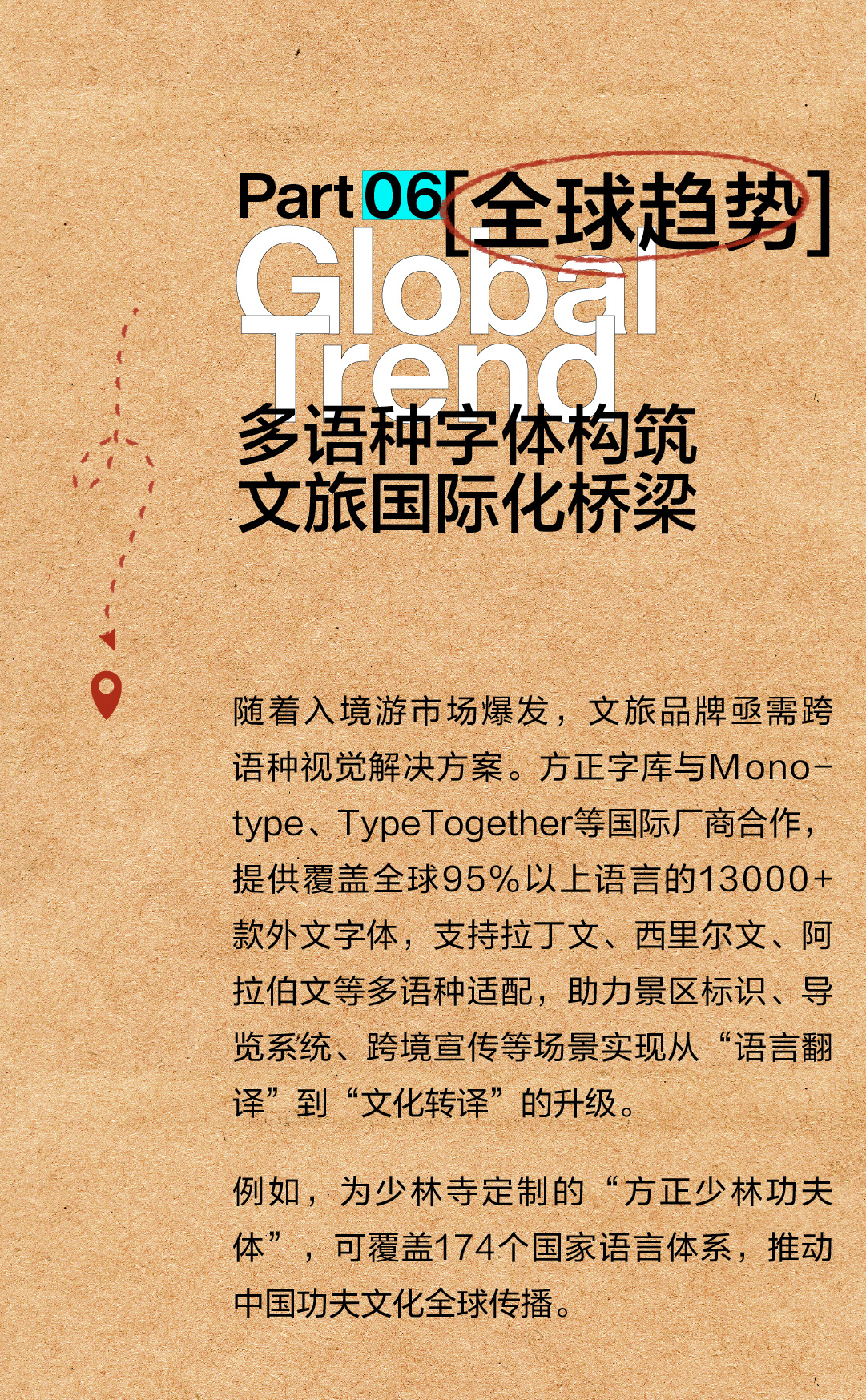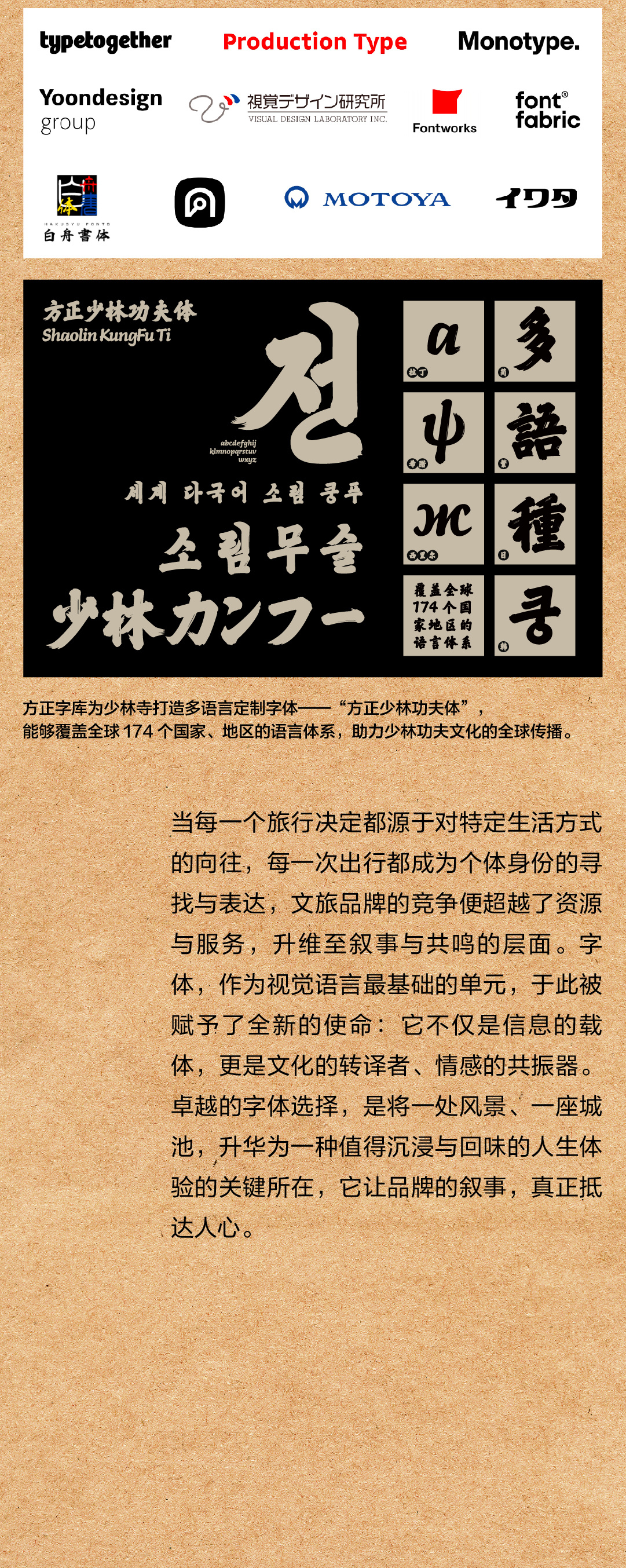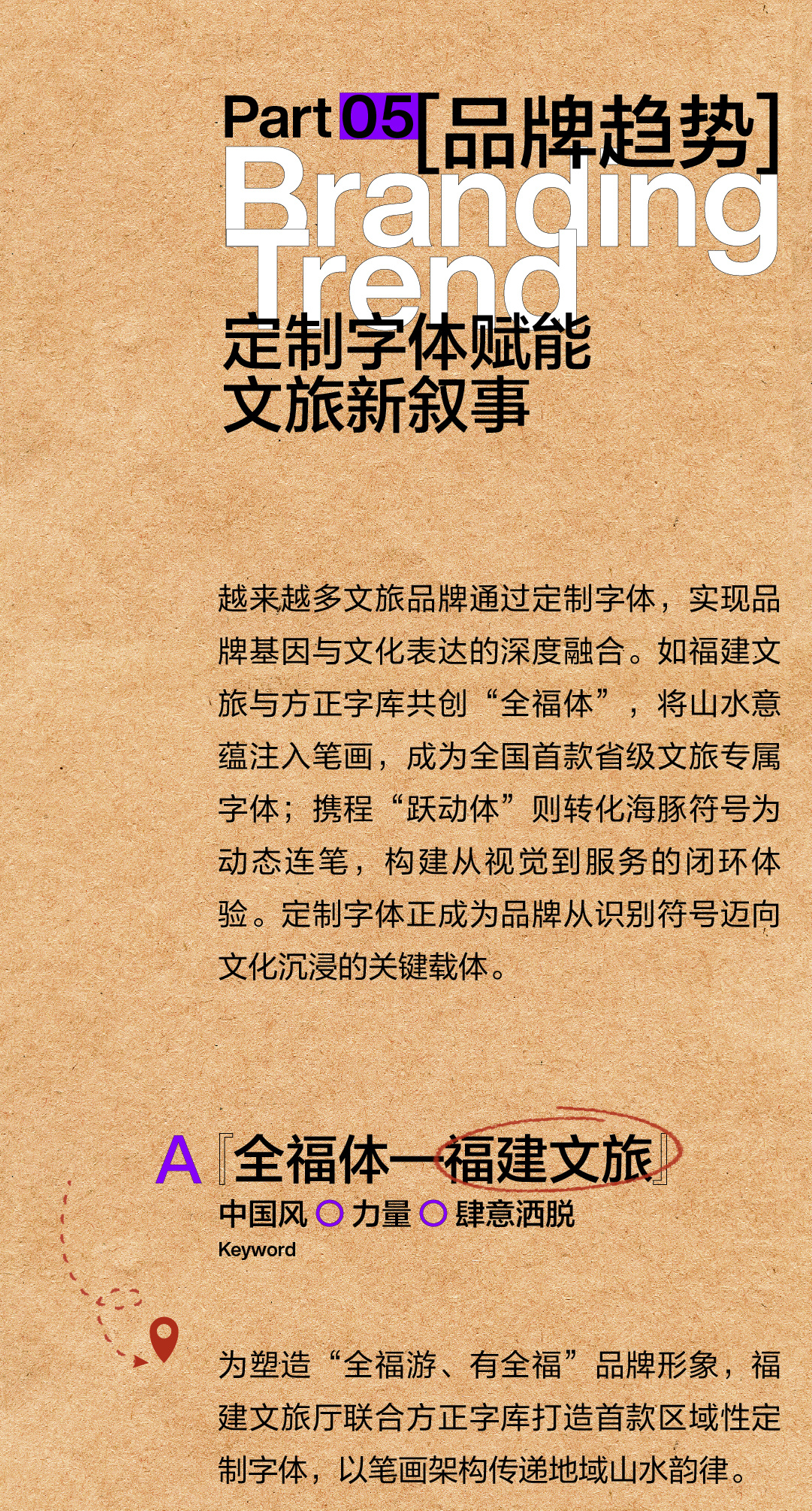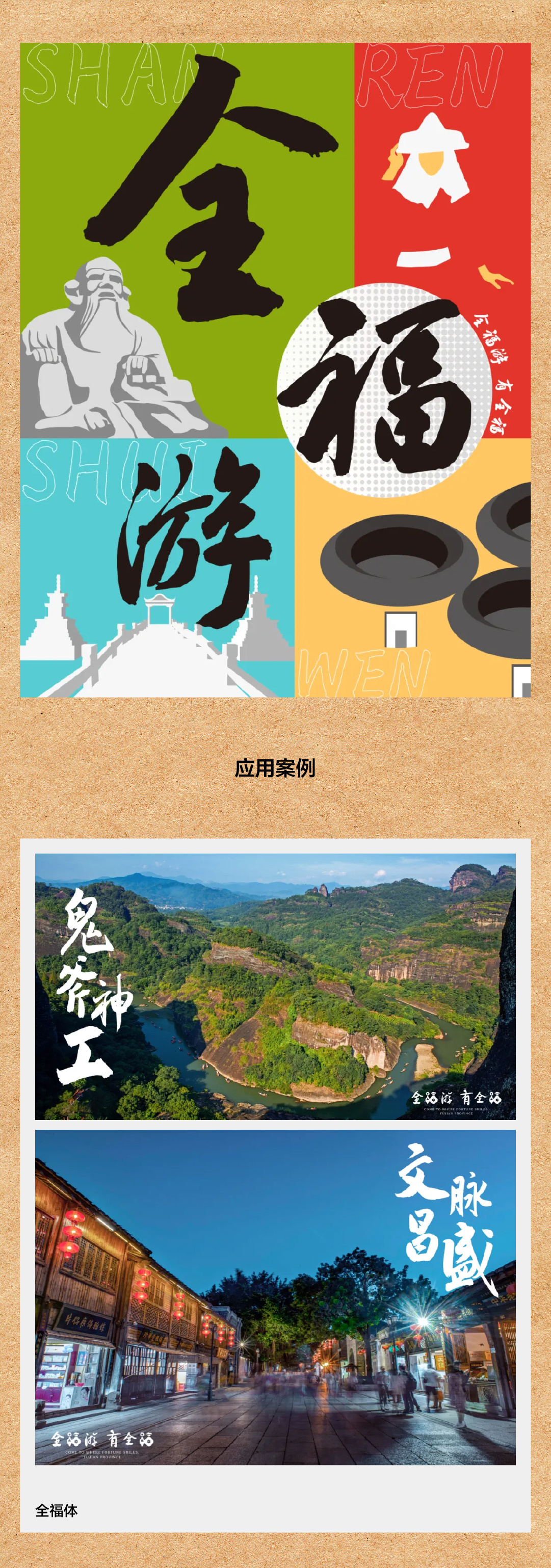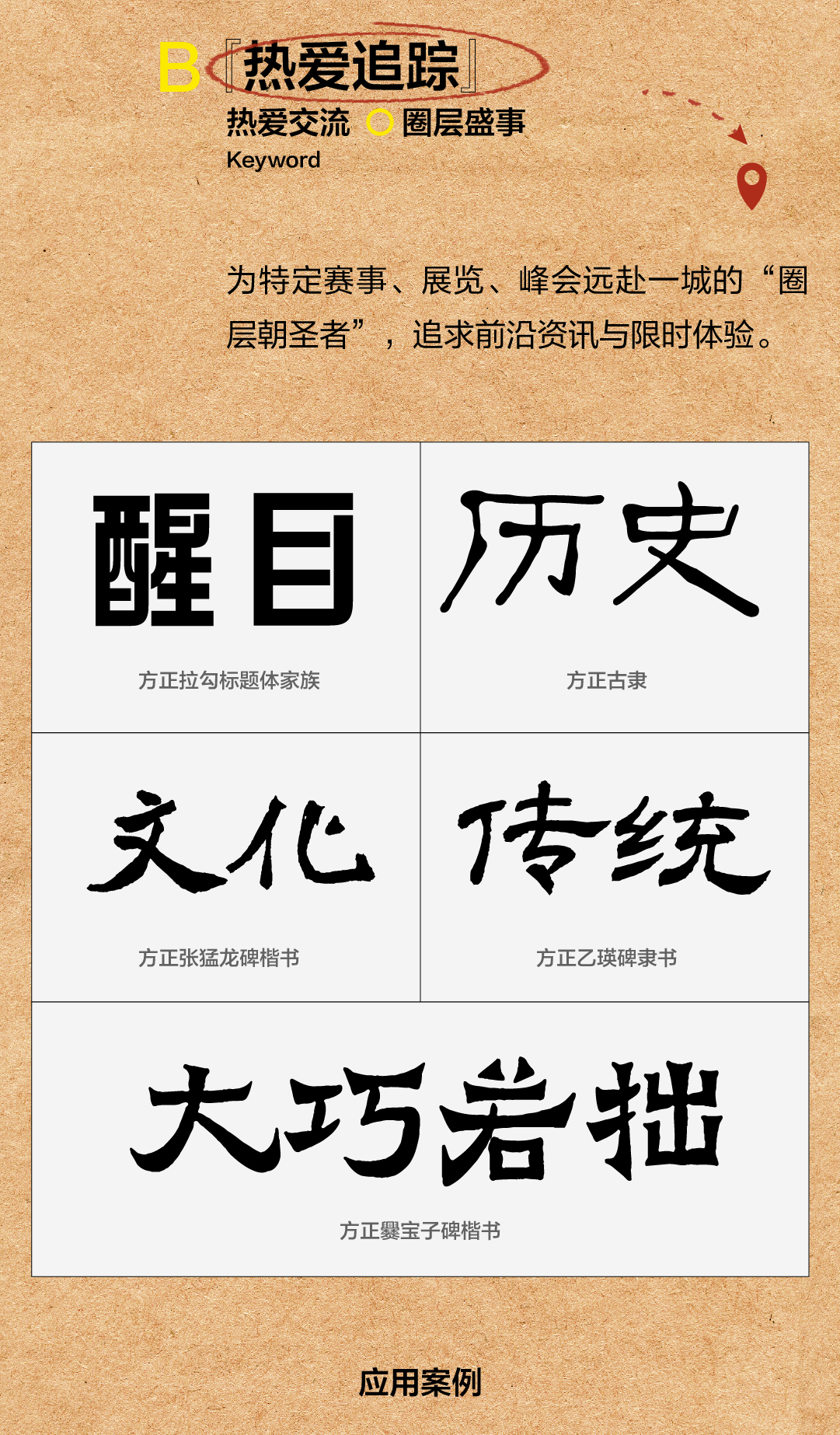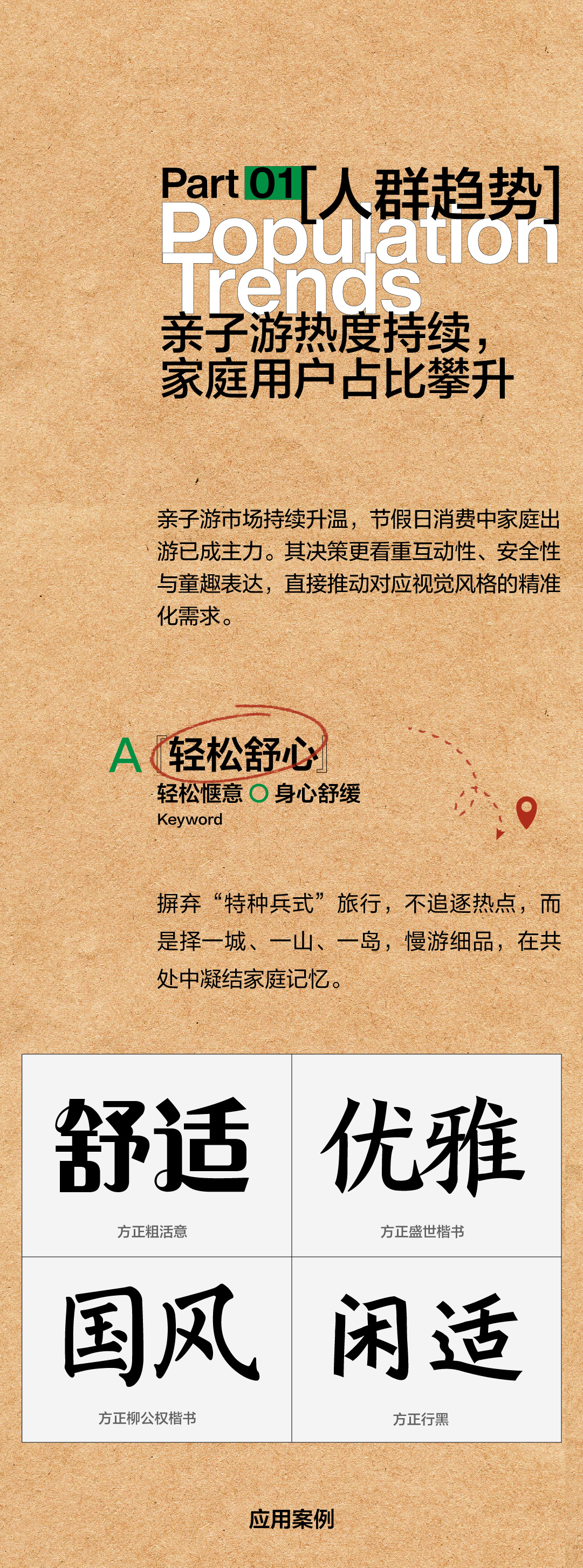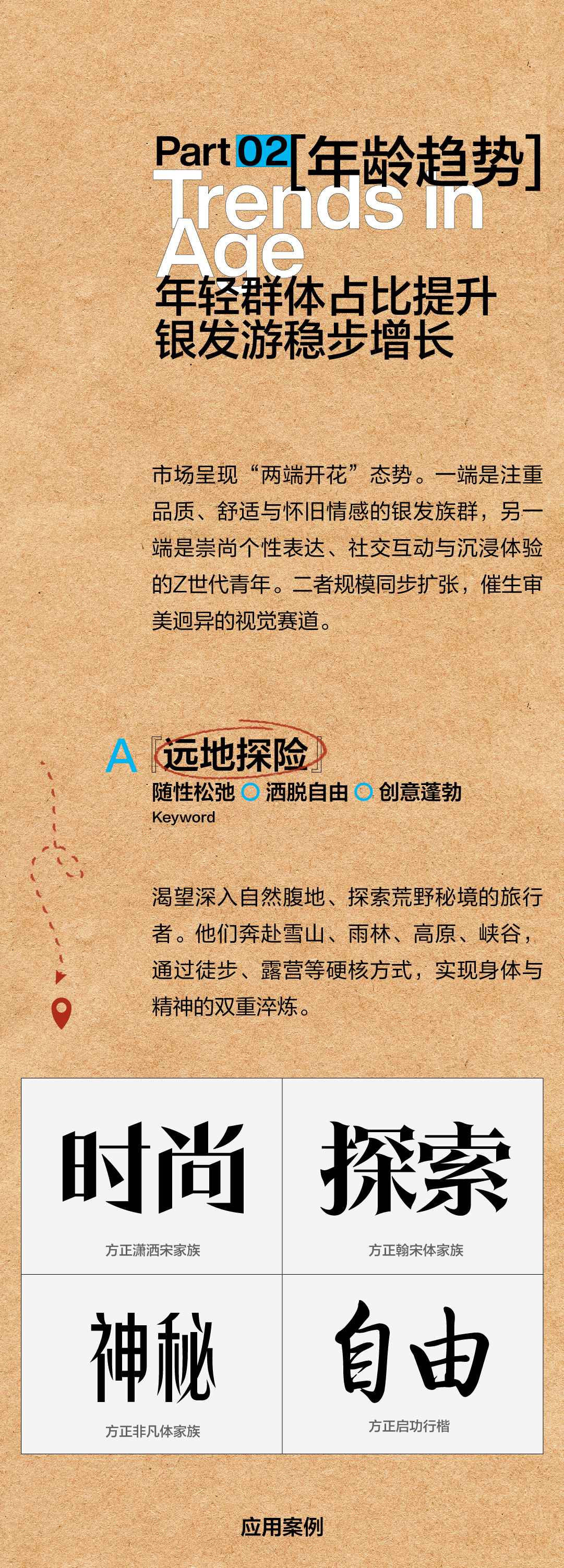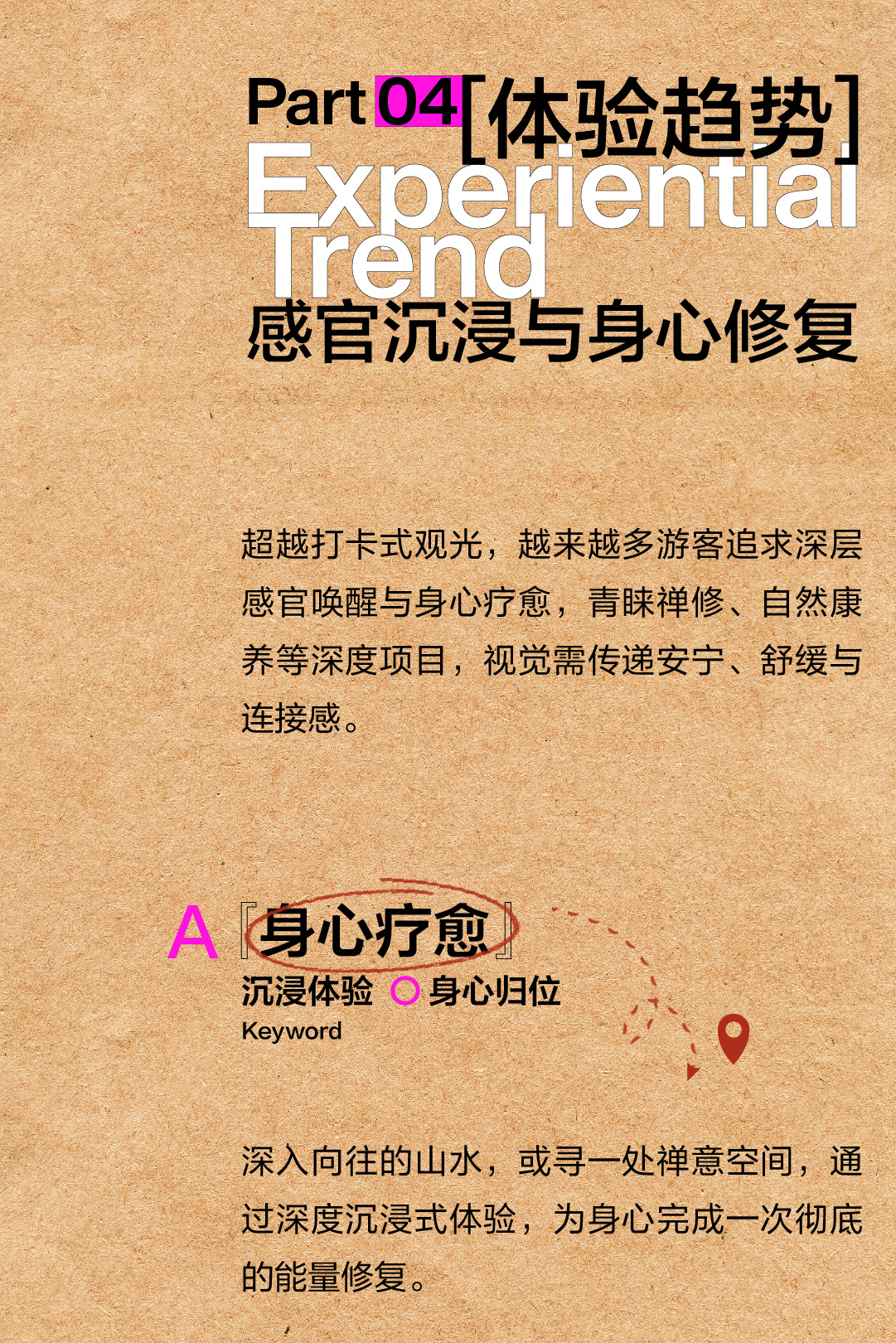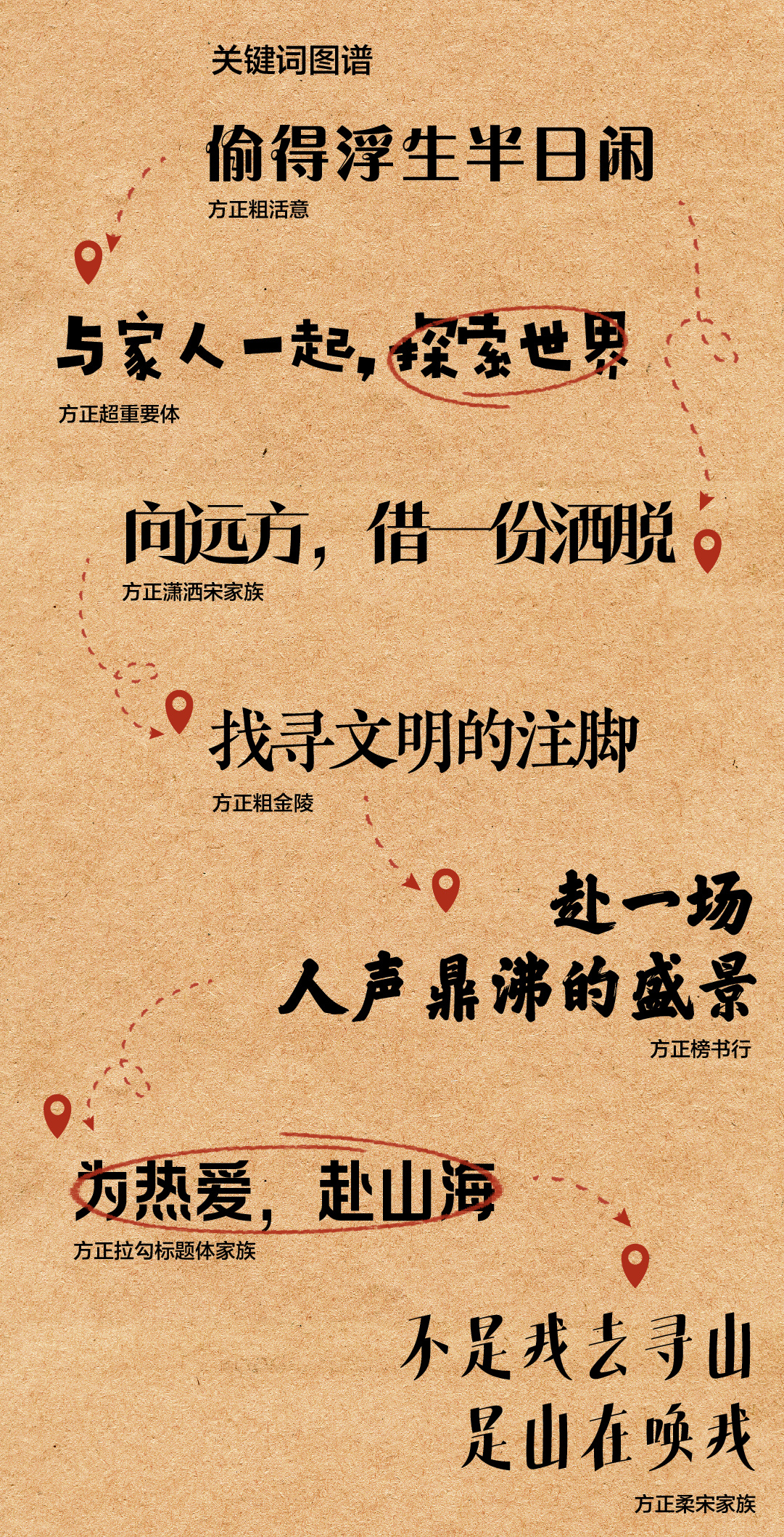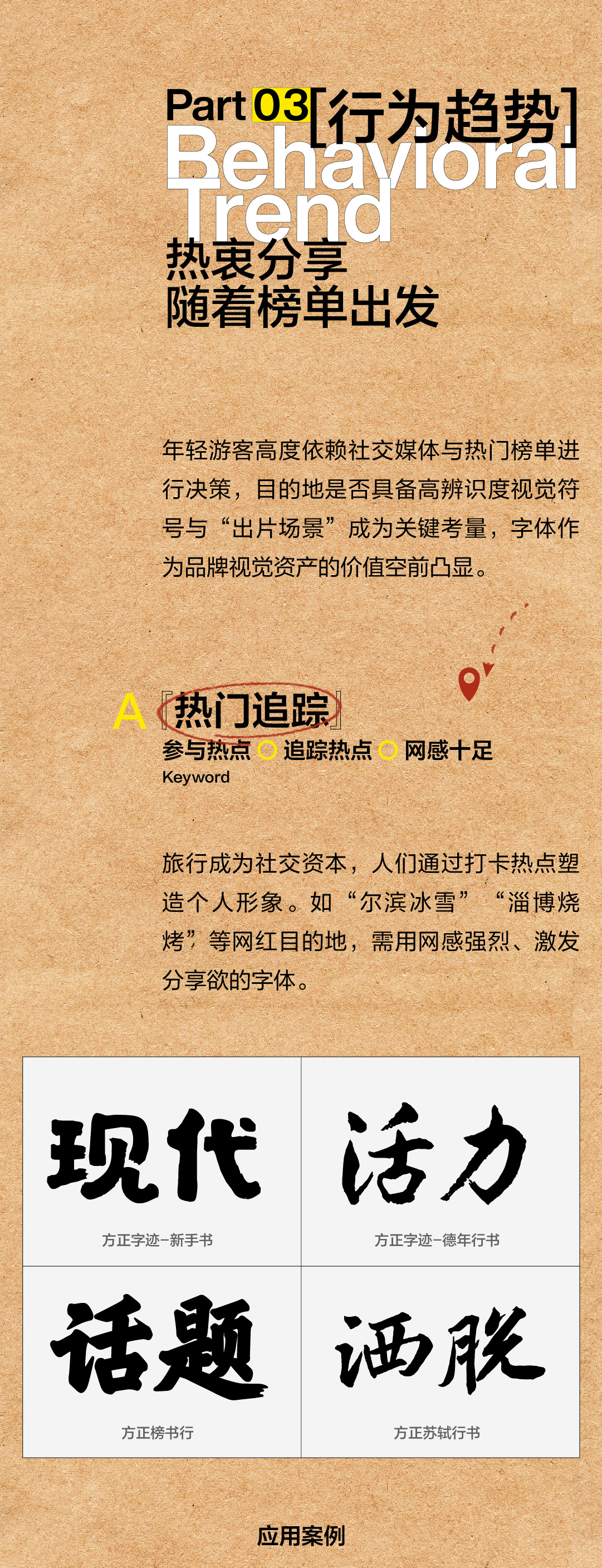
2025文旅新风向:用字体为体验经济赋能
当体验经济重塑消费逻辑,当“出片率”成为年轻一代的出行刚需,当小众目的地跻身主流视野,文旅视觉传播正式迈入“情感精准触达”的时代。字体,不再仅是美学附庸,而是品牌战略的核心资产,折射出行业从规模化观光向个性化、主题化度假转型的深刻变迁,最终催生多元风格交织、高度细分化的视觉新范式